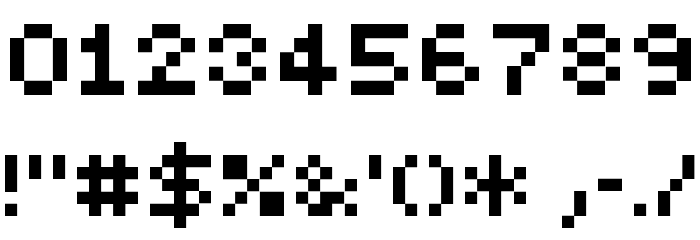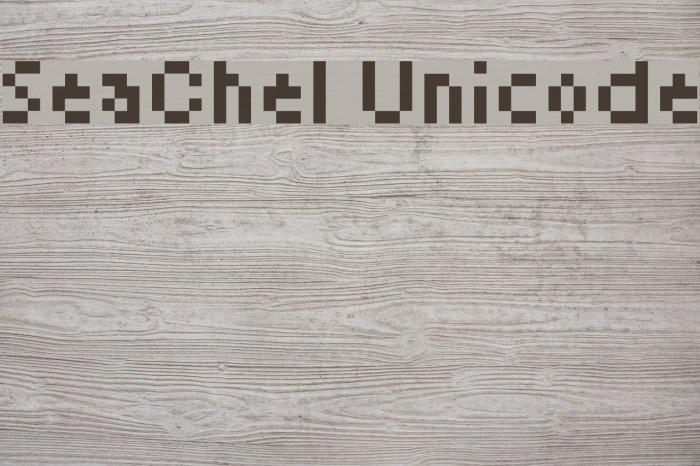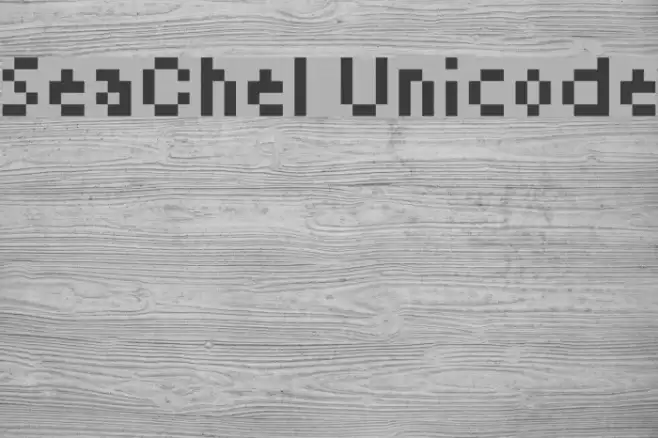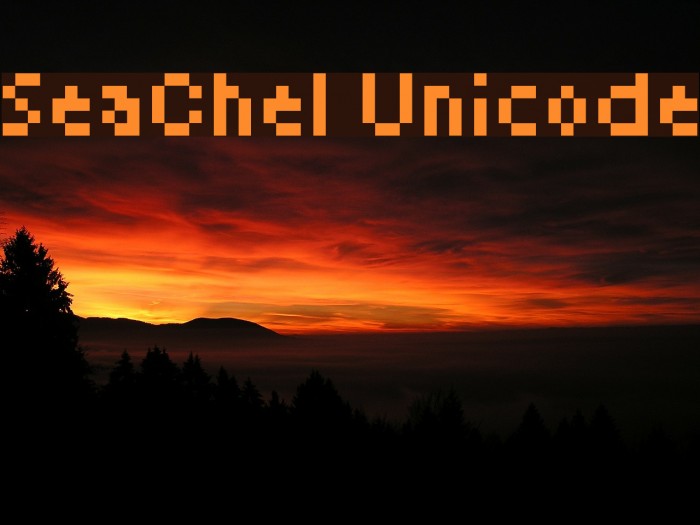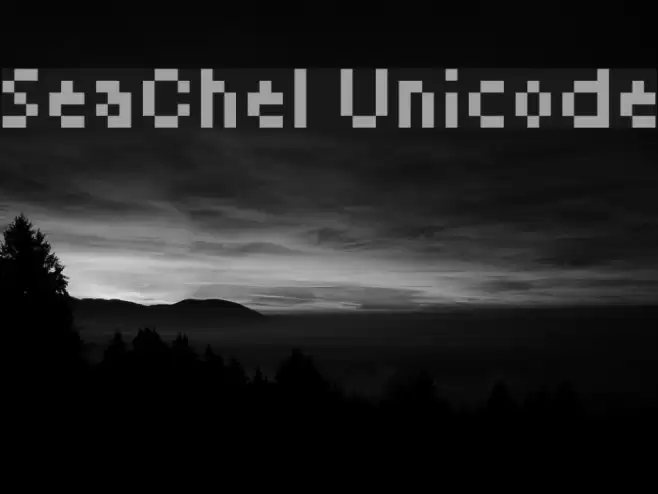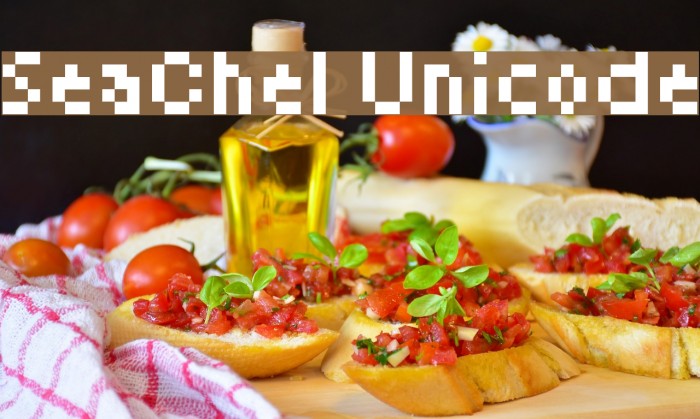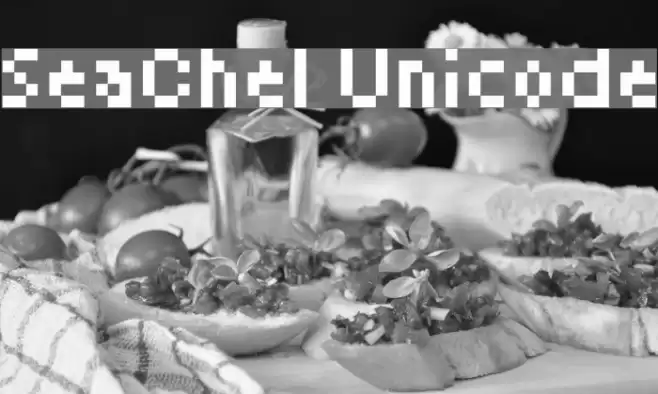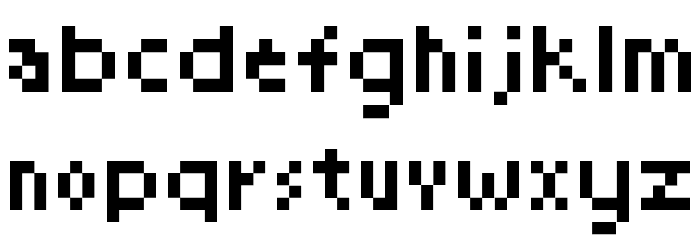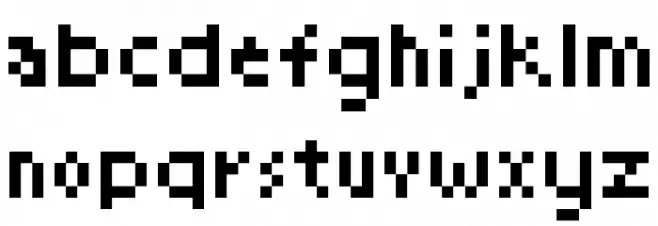
SeaChel Unicode Font
| Категория | Pixel |
| Общий стиль | Retro, Digital |
| Область применения | Logos, Headlines, Digital displays |
| Рекомендуемые проекты | Ideal for retro video game designs, digital-themed posters, or any project requiring a nostalgic, pixelated look. |